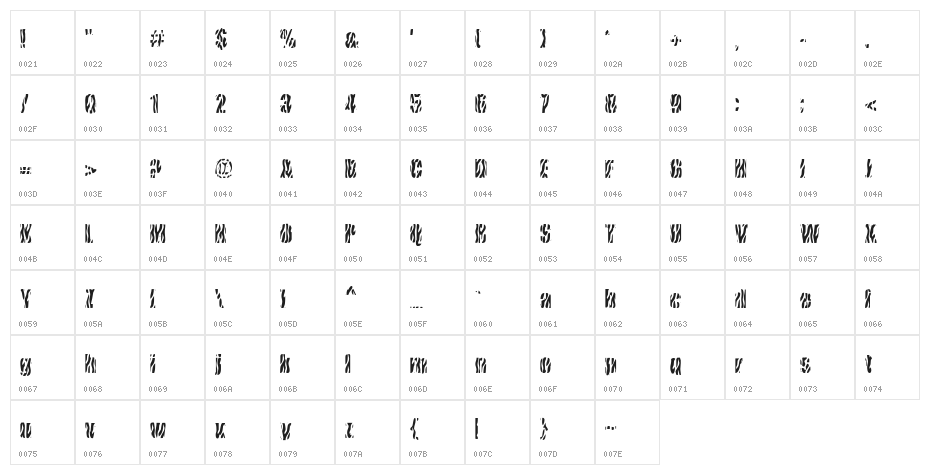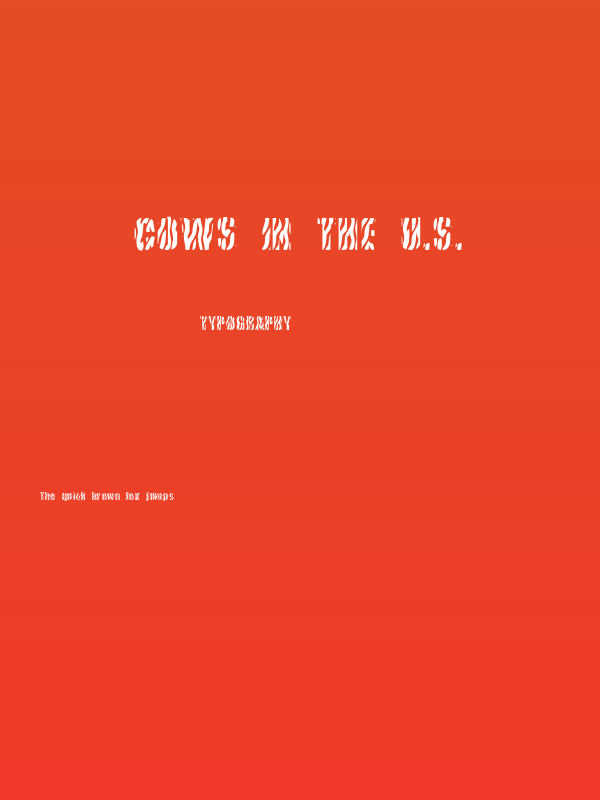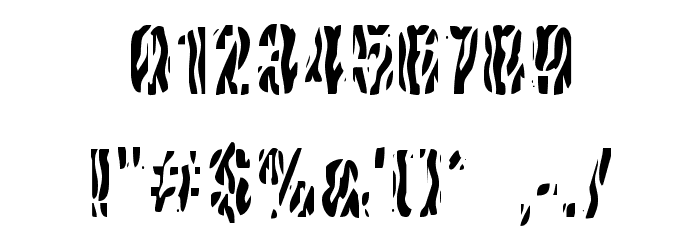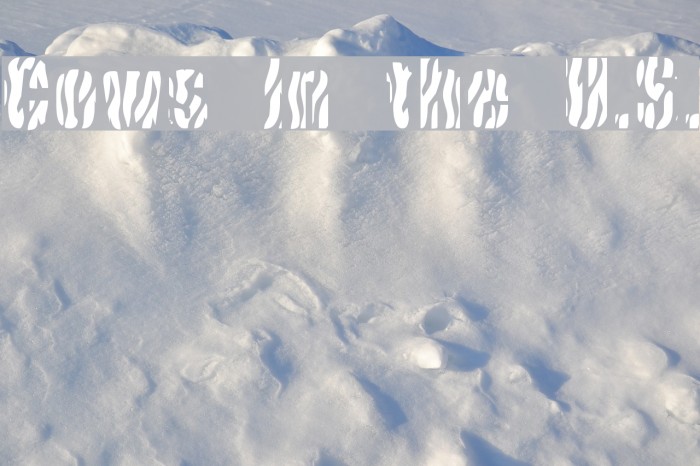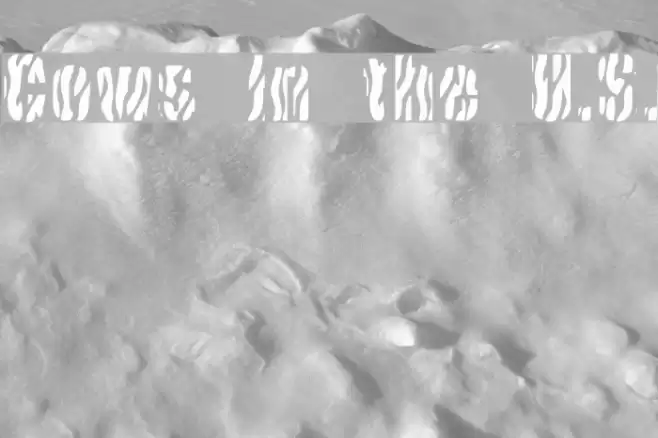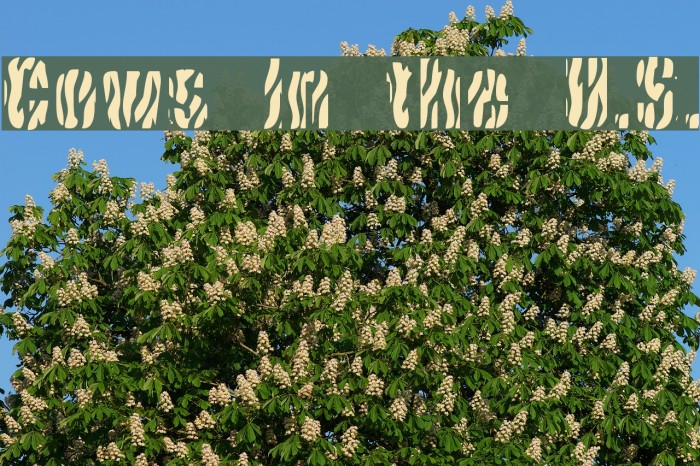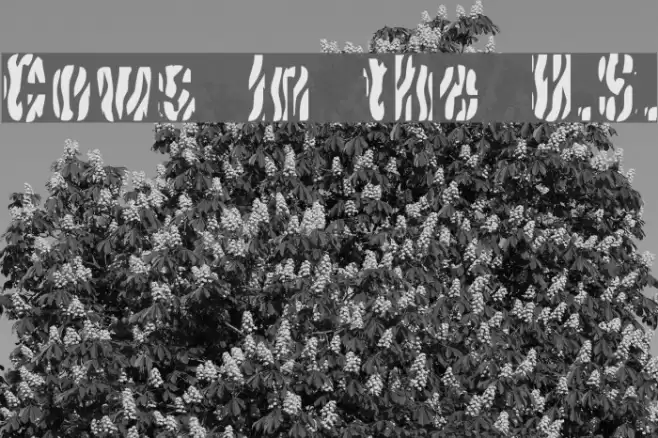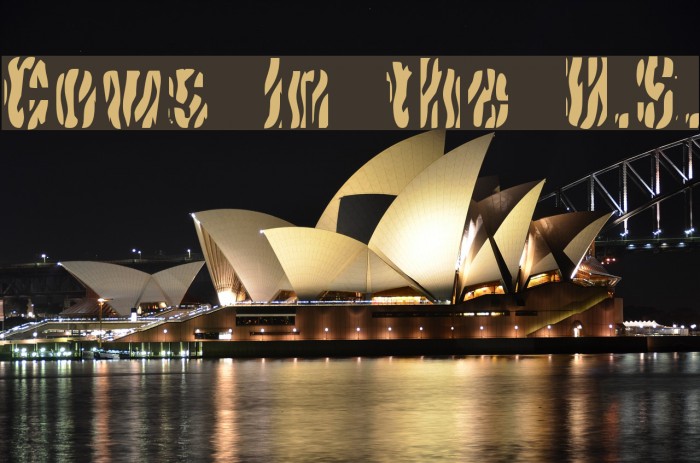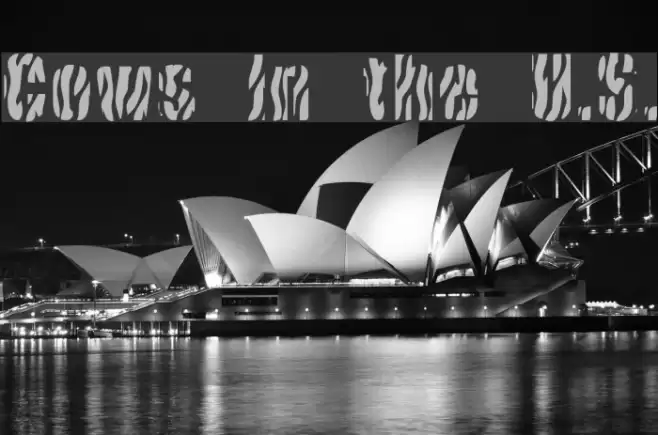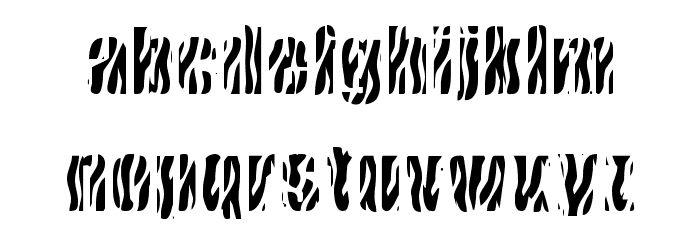
Cows In the U.S. Font
| Projetos propostos | Ideal for children's book covers, playful branding, themed event posters, or any design needing a fun and whimsical touch. |